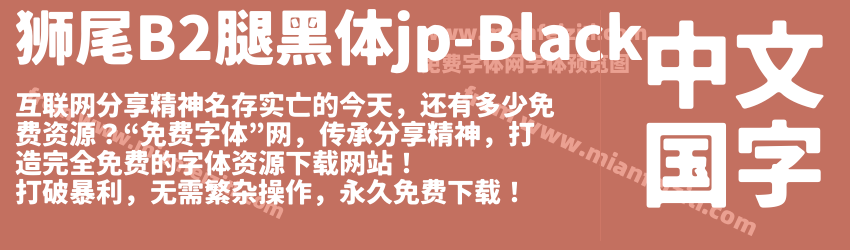
狮尾B2腿黑体:基于思源黑体的转角的三角形转成半圆形改造字体资讯
狮尾B2腿黑体基于思源黑体的转角的三角形转成半圆形改造,腿黑指没被拔脚的黑体,彷彿墨晕或是稍微过曝的效果。支援简体中文、繁体中文、韩文与日文;欢迎大家自由应用、自由优化、自由改作!
狮尾B2腿黑体jp-Black字体预览
狮尾B2腿黑体jp-DemiLight字体预览